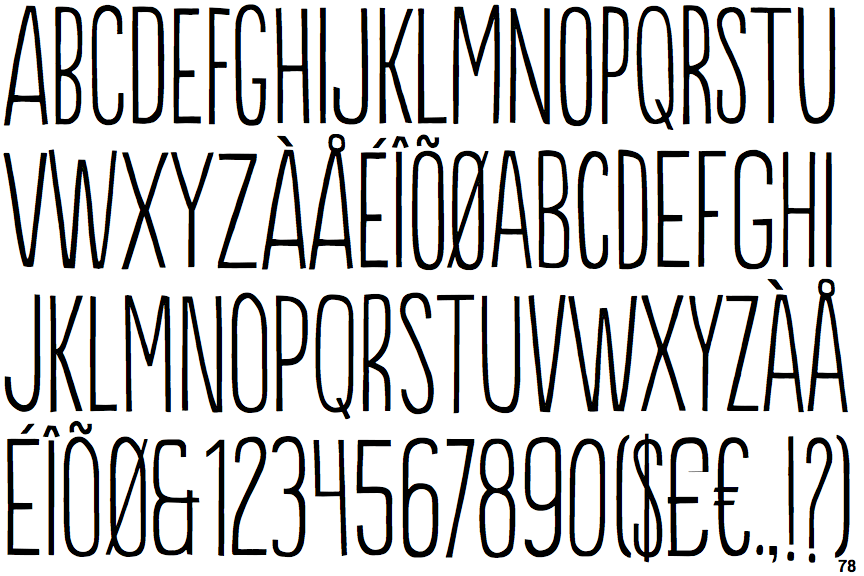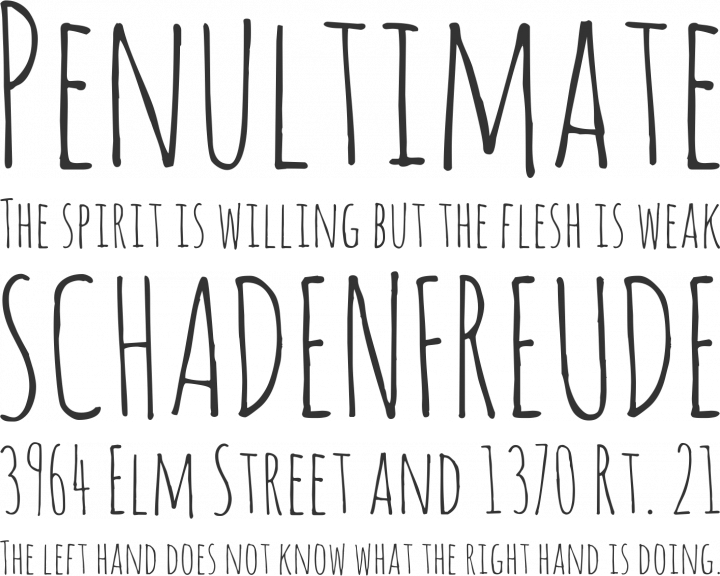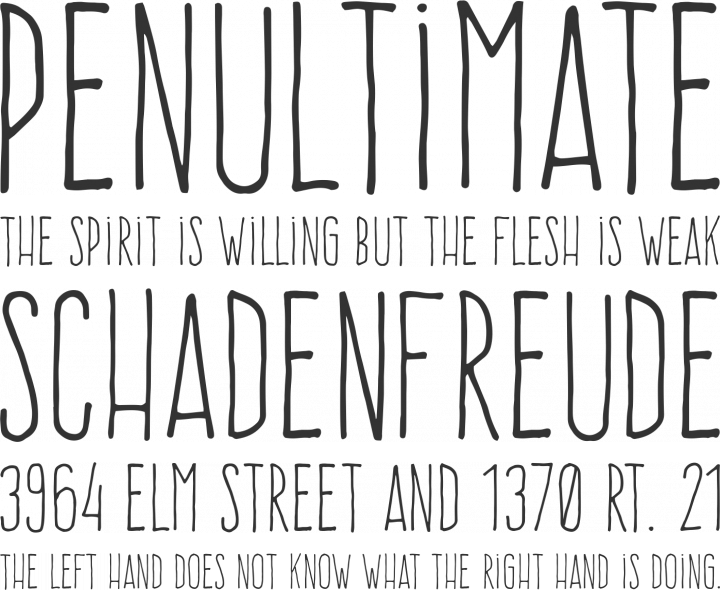
Modewelle: Condensed Comic-Schriften in All Caps und Small Caps für Nahrung, Gaststätten und Genuß (NGG)??
Ich habe hier eine Frage über eine „Modewelle“ und wollte dazu etwas näheres Wissen. Mein Ansatz dabei ist folgender: „Das Bewusstsein bestimmt das Design.“ Davon ausgehend verrät das Design manchmal mehr über den Auftraggeber als es die eigentliche Werbung macht.
Zuerst mal zur Modewelle und der Schriften. Die Schriften sind unregelmäßige Comic-Schriften, haben eine Anmutung von Handwerk, bis auf wenige Ausnahmen sind die Striche Markerschriften nachempfunden und die Linien enden rund. Diese Schriften sind All Caps oder Small Caps und laufen bis auf wenige Schnitte sehr schmal.
Hier zuerst eine Schrift die bei REWE verwendet wird und als Ausnahme keine unregelmäßige Handschrift ist. Sie hat gerade Linien und diesen enden eckig:
Typeface: Populaire
Designers: Ricardo Marcin and Erica Jung
Year:  2012
Publisher: Pintassilgo Prints
No lower-case characters.
Ein weitere Beispiel, welches ich gesehen habe:
Typeface: Aracne und Aracne Condensed
Publisher: Antipixel
Year:  2012
Designer: Julia Matrinez Diana
Hier zwei sehr beliebte, (auch für kommerzielle Nutzung) echt freie(!) Schriften mit Marker-Duktus:
Typeface: AmaticSC
Designer: Vernon Adams
Typeface: FrenteH1
Die grafischen Elemente sind sehr häufig nur einfach(st)e Formen, wie einfarbige Kreise und Rechtecke/Quadrate, auf denen dann die Schrift (ggf. Invers/Weiß) erscheint. Das Design wirkt eher leicht, kindlich und freundlich.
Fragen:
- Wem sind diese Merkmale schon bewusst aufgefallen?
- Wann sah sie/er das erste Mal dieses Design?
- Welche Produkte wurden damit wann beworben?
- Wann ist das Design in welchem Kontext aufgetaucht?
Mir ist dieses Design im Bereich NGG (Nahrung, Gaststätten und Genuß) ab 2014 immer stärker aufgefallen: Essen, Kochbücher … Dabei bin ich beim Suchen nur wenig vor 2014 gekommen und dieses Design kam damals (bis auf sehr wenige Ausnahmen) aus den kommerziellen Bereichen. Es war häufig an extreme Gewinnerzielungsabsichten, teilweise über die Grenzen der guten Sitten hinaus, verknüpft. In einem anderen Kontext jenseits NGG habe ich dieses Design noch nicht wahrgenommen. Daher noch eine Frage: War das Zufall, schlechte Recherche und/oder nur selektive Wahrnehmung von mir?
PS: Ich hatte eine sehr ähnliche Erfahrung mit der FF-Meta. Ab etwa 2008 fiel mir diese als Schrift für das Vermitteln von Lug und Betrug auf und ich konnte damals als ungefähren Beginn der Modewelle 2002/2003 ausmachen. Allerdings wurde nach 2008 die FF-Meta schon wesentlich vielseitiger verwendet und es gab da schon keine so eindeutige Zuordnung mehr.
Fragen:
- Wem sind diese Merkmale schon bewusst aufgefallen?
- Wann sah sie/er das erste Mal dieses Design?
- Welche Produkte wurden damit wann beworben?
- Wann ist das Design in welchem Kontext aufgetaucht?
Mir ist dieses Design im Bereich NGG (Nahrung, Gaststätten und Genuß) ab 2014 immer stärker aufgefallen: Essen, Kochbücher …
Mir auch, insbesondere die wirklich schlechten bei Mc’n, wo man sie ja eigentlich gerade nicht vermutet.
Sieht man übrigens  auch am Entstehungsdatum einiger gut gemachter Vertreter diese Genres:
Naja, und bis dann die Grafikergemeinde mal soweit ist und die ersten Ripp-Offs bei Dafont hochgeladen sind, ist es eben 2014. ;-)
Aber eine »Verschwörungstheorie« vermute ich dahinter nicht. Das ist eben der ganz normale Wahnsinn von Trendhopping™ und Andersmaching™.
Ich sehe da auch eine Parallele zu den Stempeloptik-Schriften ... das alles soll »handgemacht« assoziieren. Das ist weniger Auslöser als Symptom einer zunehmenden DIY-Affinität, vielleicht auch zeitgleich mit dem Erblühen von Dawanda und DIY-Blogs ... die Verwendung im Nahrungsmittelbereich habe ich da erst später wahrgenommen.
Mürrischen KulturpessimistInnen fällt manches auf, was dem unkritischen Konsumenten nicht auffällt, ihn aber manipuliert... ;-)
Ich denke auch, dass das einhergeht mit der Shabby-Chic- und DIY-Welle. Wann das genau anfing wird man nicht sagen können, das sind eben Wellen und die Übergänge fließend. Erst kamen diese Schriften und schon ist das Netz voll mit DiY-Lettering-Tutorials und Menschen die das bei Dawanda verkaufen (wollen). Pessimistisch sehe ich das auch nicht. Wie R::bert schon sagte, ist das der normale Wahnsinn und ich sage mal jedem, der sich mit Design befasst, sollte dieser Trend schon lange aufgefallen sein. Den meisten anderen Menschen auch, nur können sie es eben oft nicht so beziffern. Vorweg war übrigens schon dieser Trend mit den unfertigen Krickelillustrationen, die, wie ich denke, den Weg für diese Schriften geebnet haben. Diese Entwicklungen kann man auch sehr gut im Editorial-Design beobachten, bevor sie in die Werbegestaltung überschwappen™. Ich bin gespannt wie die nächste Welle aussieht – wieder technischer, Neonfarben wie in den 80ern? Man wird sehen …
Neon ist, glaube ich, gar nicht so schlecht geraten ;-)
Jedenfalls denke ich auch, dass die Großen hier einfach auf einen Trend aufspringen, nachdem plötzlich jedes Bier und jeder Burger »gecraftet« wird.
Zeitschriften, die gezielt mit solchen Schriften arbeiten: Good Health, Lecker, Mutti, … Dabei dürfte die Lecker im Hause Bauer damit angefangen haben, soweit ich mich entsinne.
Ganz groß dabei: Flow. Letztens gab es auch ein Gimmick-Heftchen mit Anleitungen zum Lettering™ – das habe ich hier irgendwo rumliegen (muss mich ja auch fortbilden  :hammer: )